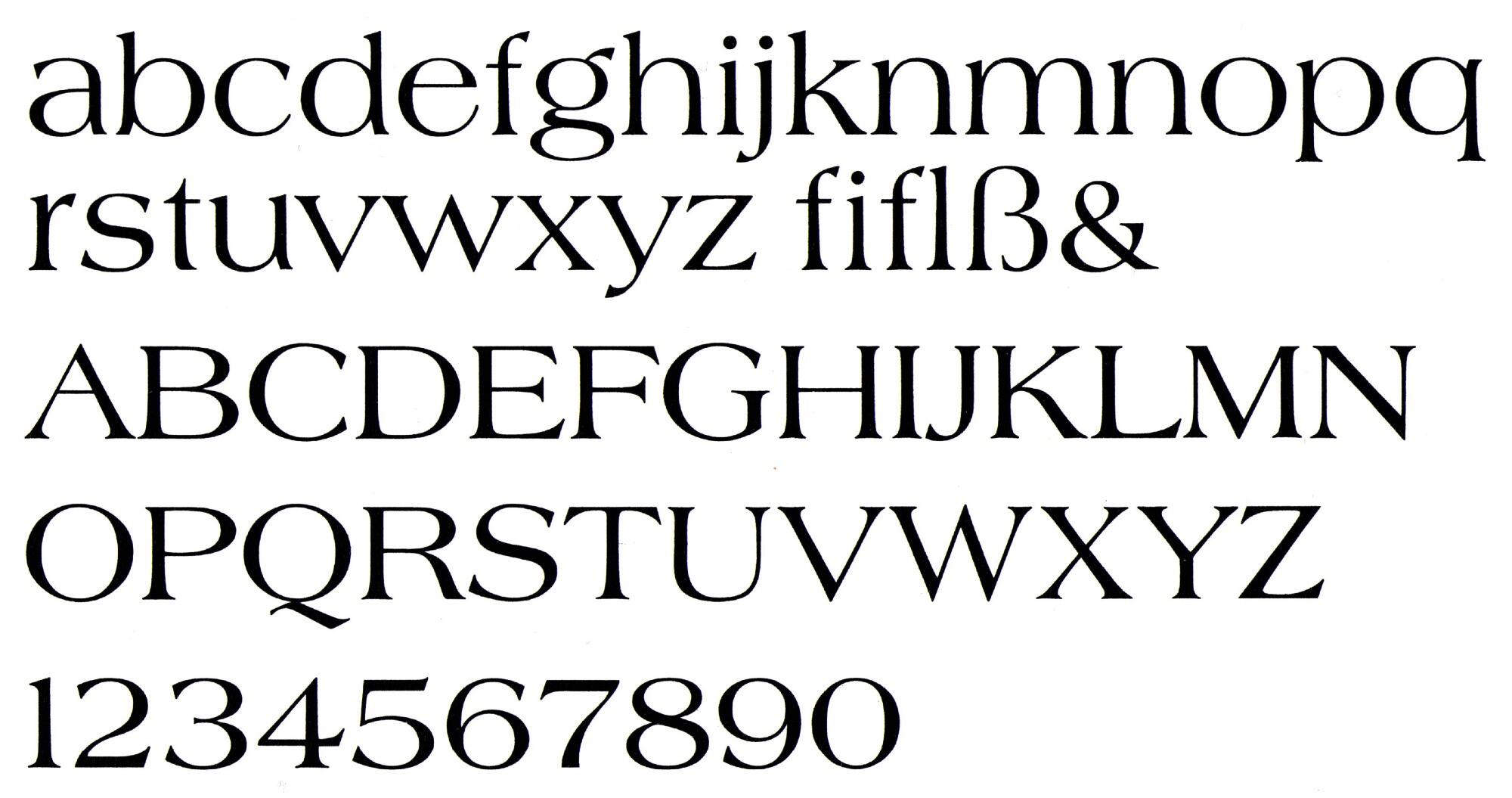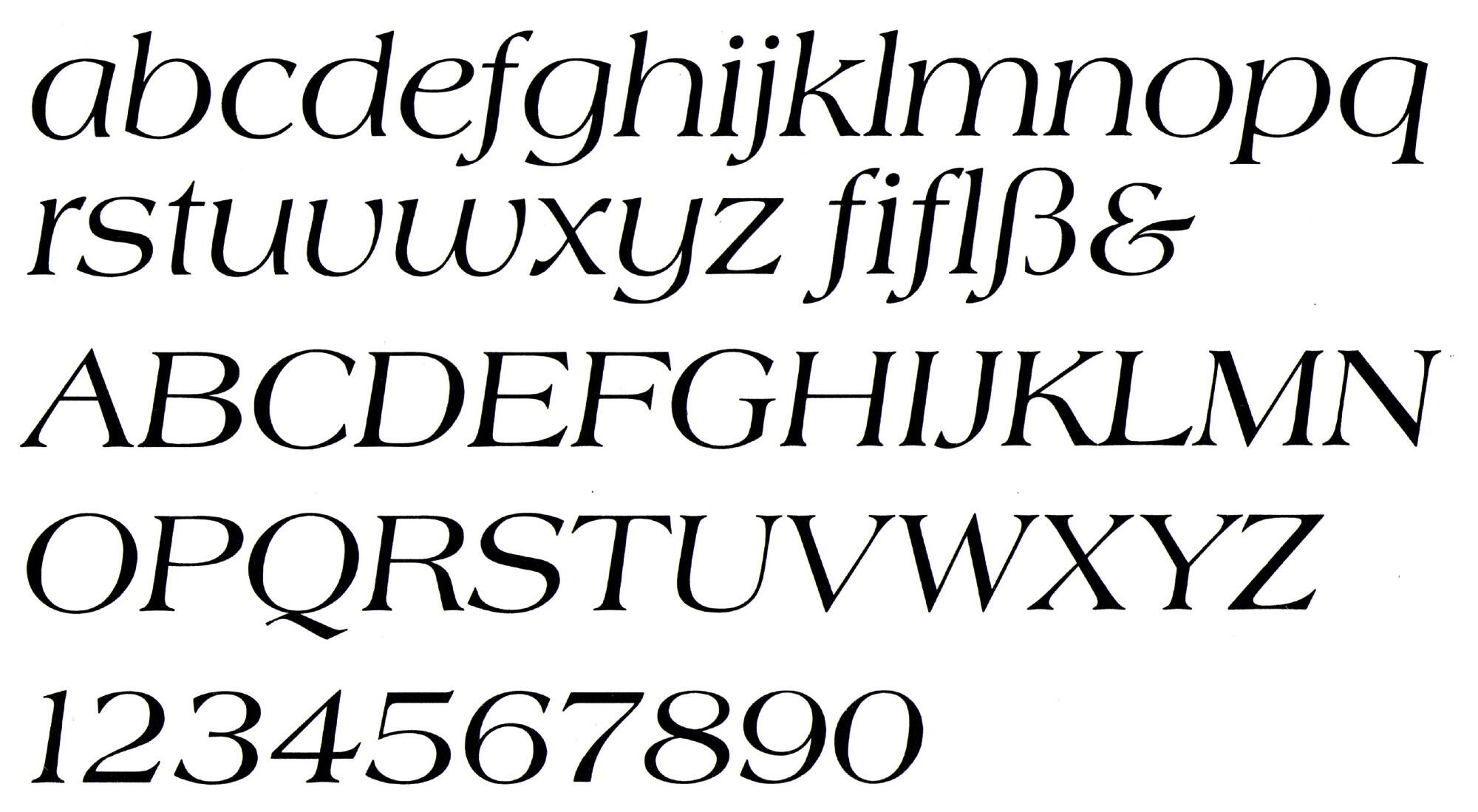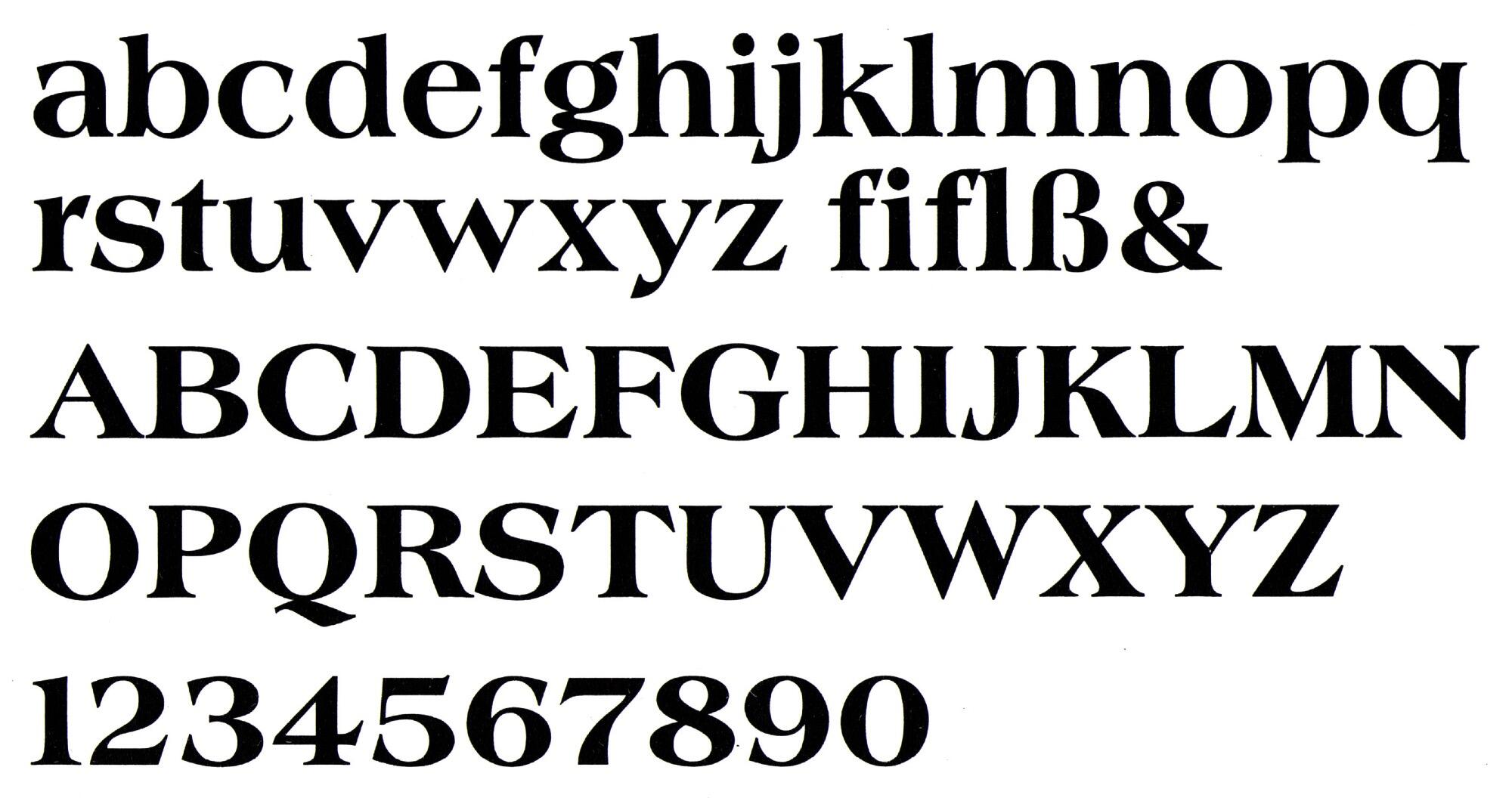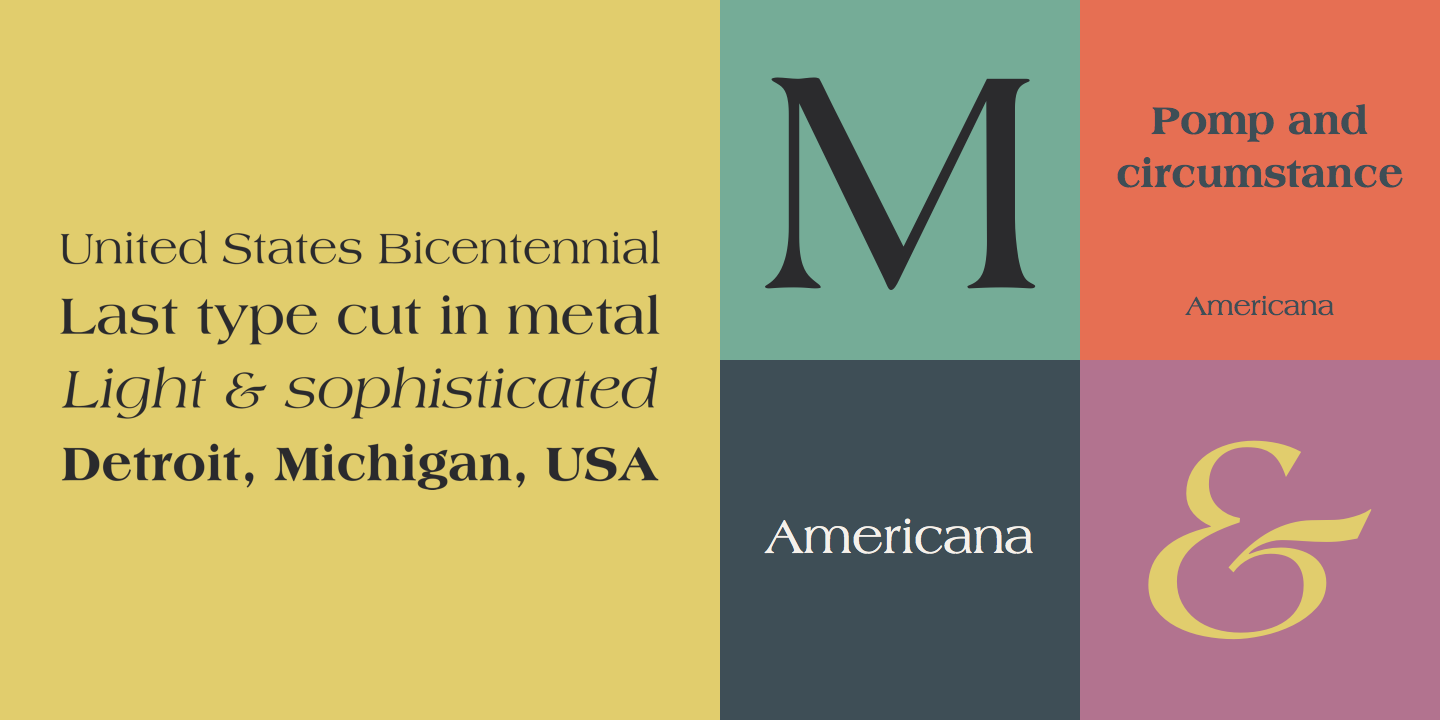
Die Americana von Richard Isbell erschien 1966 bei American Type Founders und war damit eine der letzten ATF-Bleisatzschriften. Die Schriftfamilie bestand ursprünglich aus drei Strichstärken und einem kursiven Schnitt.
Es entstanden später zahlreiche Adaptionen für den Foto- und Digitalsatz, teilweise auch mit weiteren Schnitten wie schmalfett und Outline.